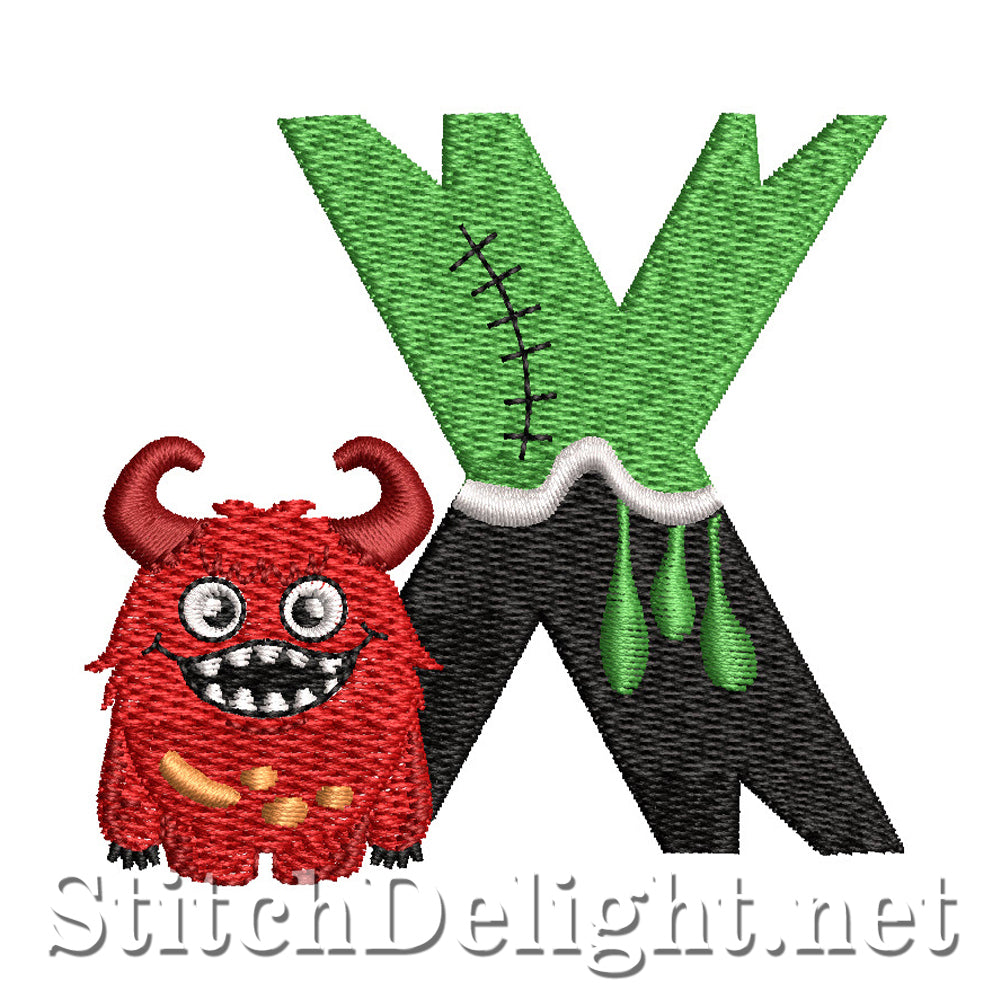
Police de caractères SDS1776 Scary Monster X
Une police effrayante parfaite pour tout projet d'Halloween ou amateur de monstres. Cette police effrayante est compatible avec les tailles de cercle 4x4 et plus ! Assurez-vous de vérifier qu'il correspond à la police SDS1777 Kiddies Font